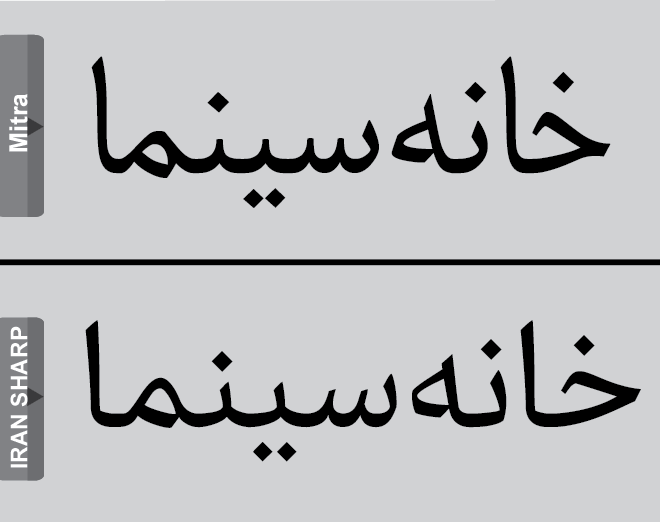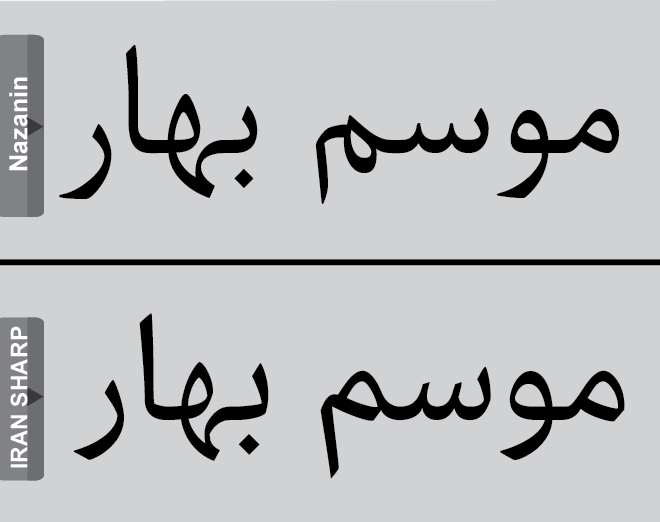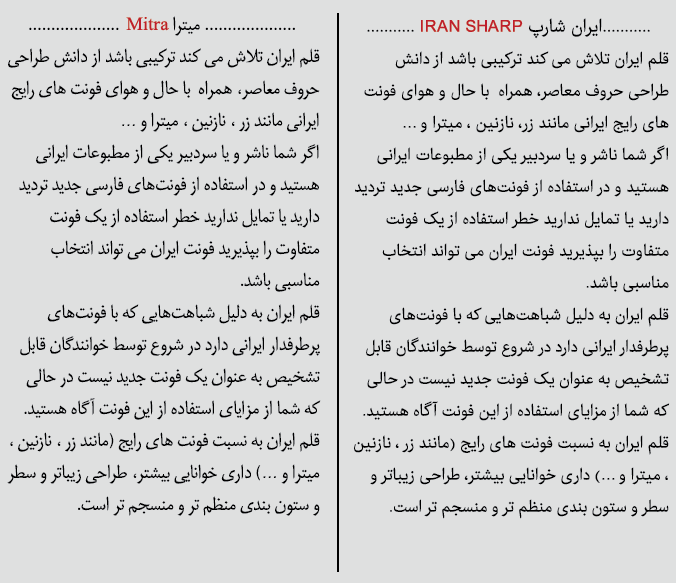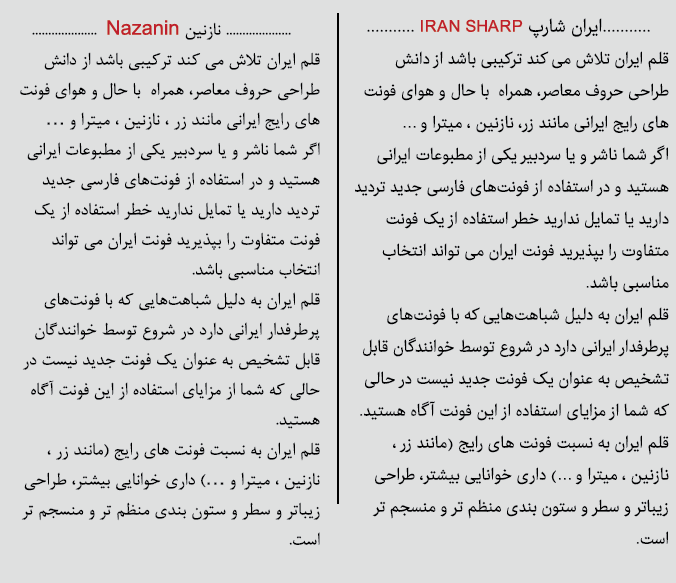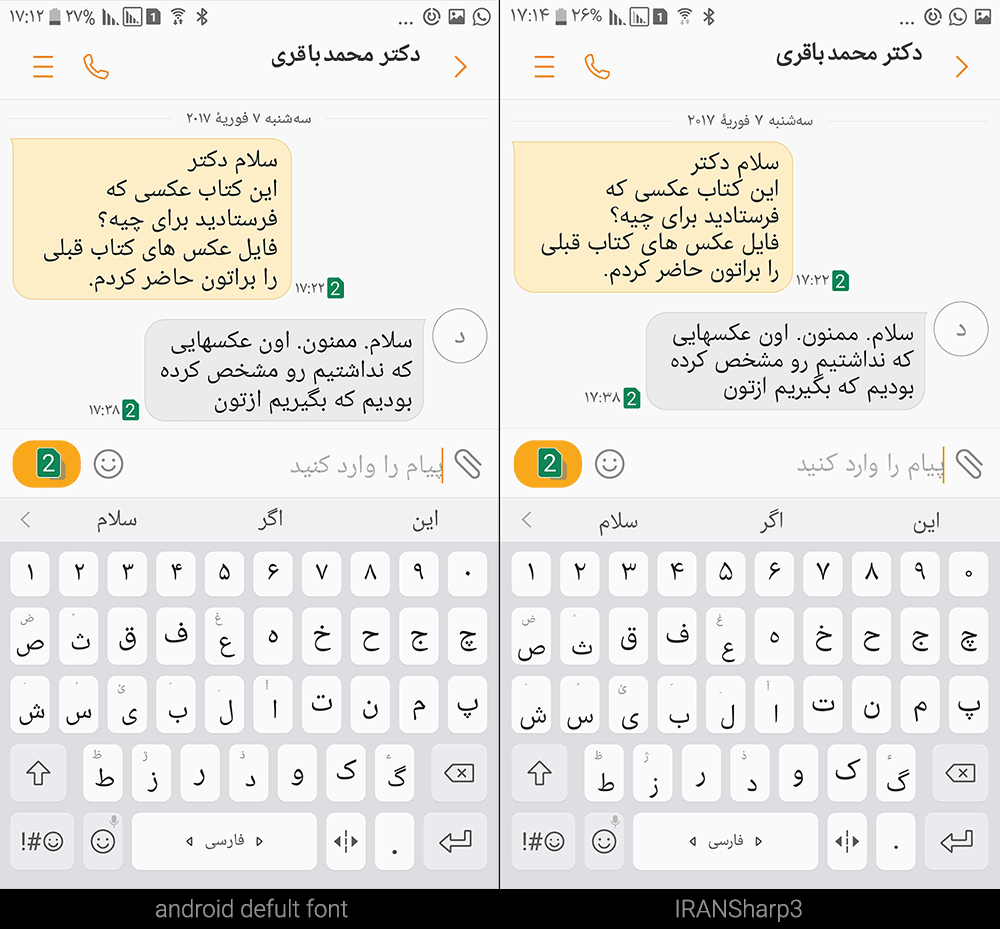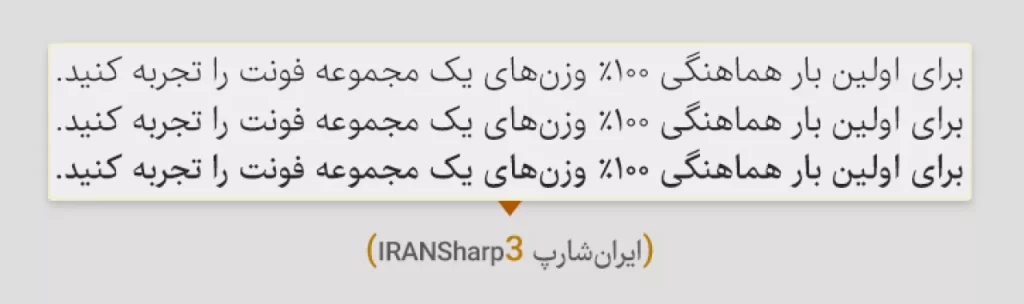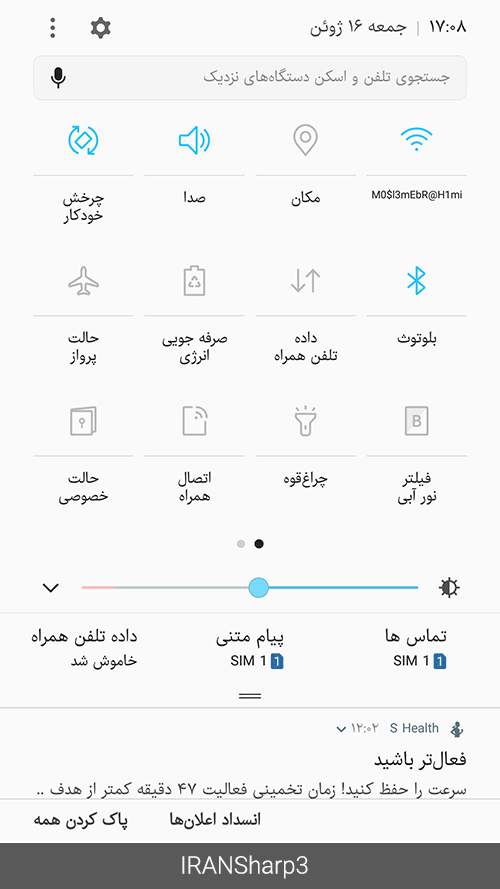
فونت ایران شارپ
فونت ایران شارپ IRAN SHARP نسخه بازسازی و بازطراحی شده تایپ فیس های زر، نازنین، میترا، لوتوس، بدر که آشنا و محبوب طراحان تایپ فارسی است. حدود نیم قرن این قلم های فارسی با طراحان و علاقه مندان تایپ فارسی همراهی نموده اند. اما از آنجایی که از دیرباز با ابزار حروف چینی های قدیمی طراحی و و ایجاد شده اند و اگرچه در این مدت تغییرات فنی هم در شاکله آنها شکل گرفته اما همچنان دارای مشکلات اساسی و قدیمی هستند.
قلم ایران شارپ توسط طراح و خالق فونت ایران آقای مسلم ابراهیمی ساخته و ایجاد شده است. این تایپ فیس نسخه باز طراحی شده اساسی از قلم های مذکور است. که مهم ترین چالش آن حفظ اصول و سبک فرم های طراحی این تایپ فیس ها در عین خلق تغییر مثبت و اصلاح ساختاری آنها بوده است.
حال که شما طراحان عزیز که علاقه من به فونت های زر، نازنین، میترا، لوتوس، بدر هستید می توانید از نسخه جدید این تایپ فیس ها تحت عنوان ایران شارپ بهره مند گردید. با وزن های مختلف هماهنگ برای خلق محتواهای زیباتر و به روز تر نسبت به آنچه در گذشته به کار مب بردید.
درتصاویر نمونه زیر می توانید با مقایسه ایران شارپ با تایپ فیس های نازنین، میترا، لوتوس، بدر به سادگیبه قدرت خوانایی بالا ظرافت های طراحی و زیبایی دوچندان این قلم پی ببرید. تصاویر گویای همه چیز می باشد. ایران شارپ دارای روحیه و شخصیتی جسور متین و جدی است.